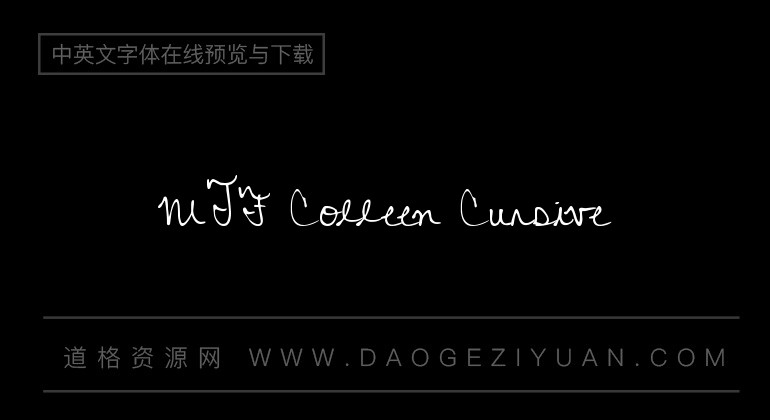
MTF Colleen Cursive
? MTF Colleen Cursive字体是一款简单优雅的手写字体,它具有柔和的线条和温暖的感觉,适合用于日常卡片或信件的制作,也可用于拼写和手写标题,拥有许多可爱的细节,可以帮助您创建一个独特而又有趣的设计。它适合用于各种文档,包括卡片,信件,小册子,礼品标签,海报和宣传单等。
MTF Colleen Cursive是一款非常不错的手写艺术字体,具有很好的视觉感,适合于文化类的宣传设计、商业类品牌的广告和产品包装设计以及个性化文字排版等较多场景。